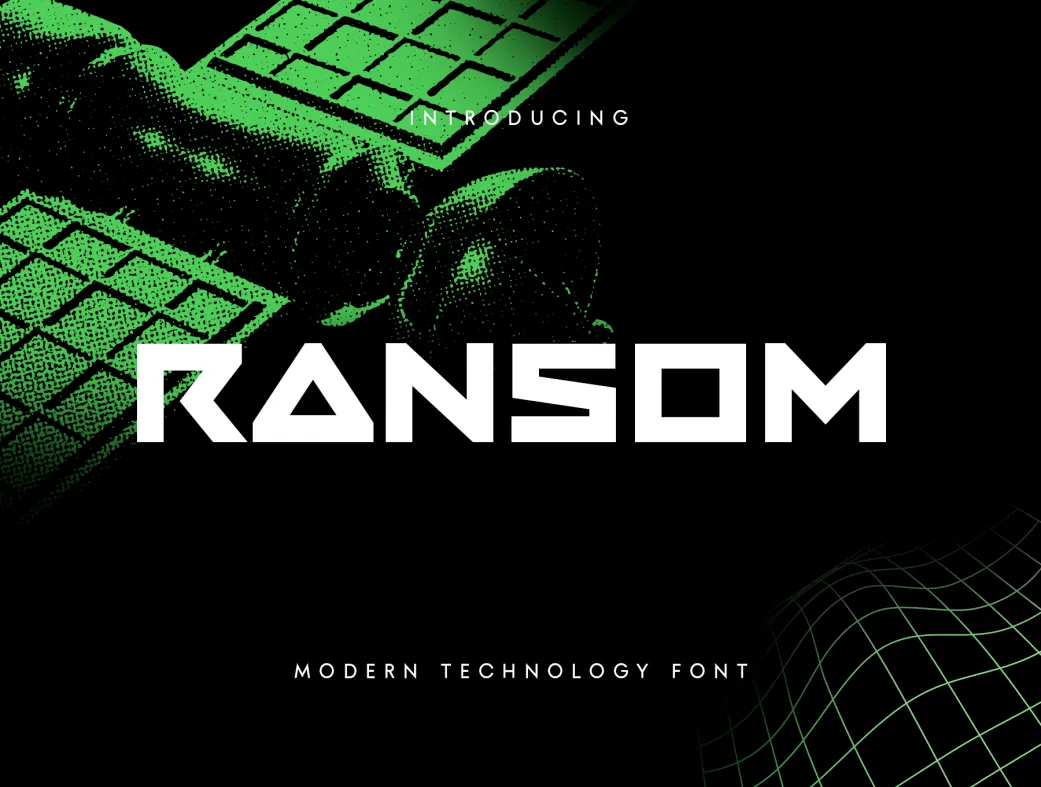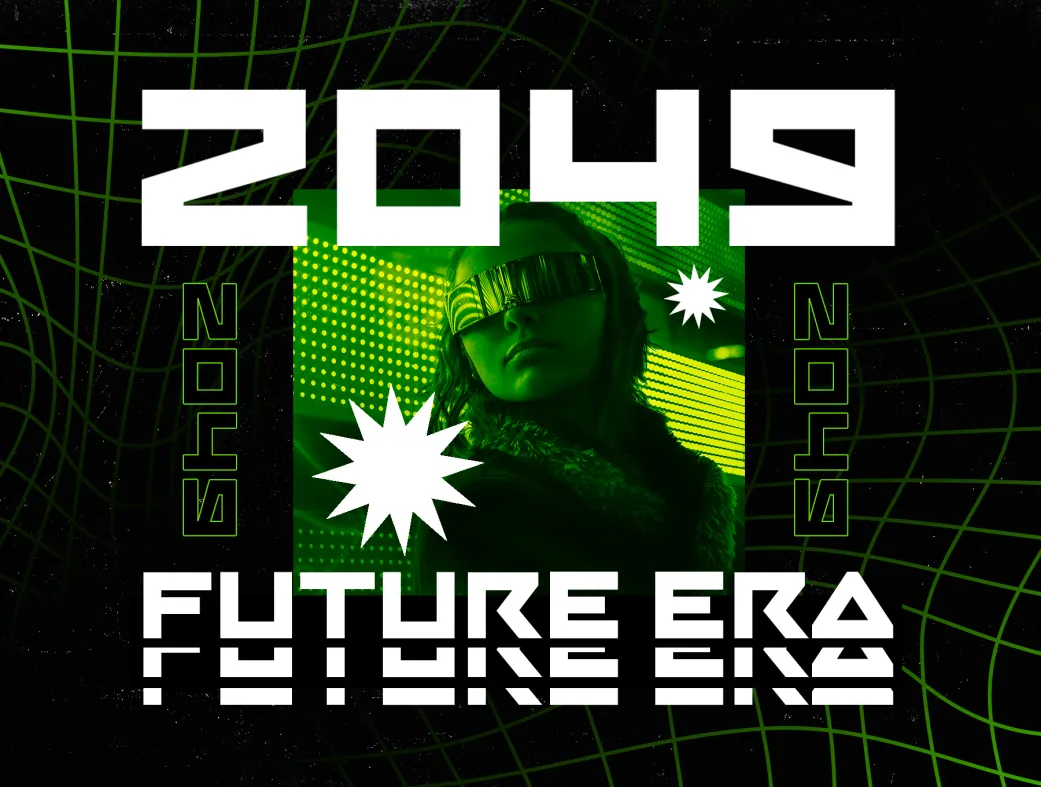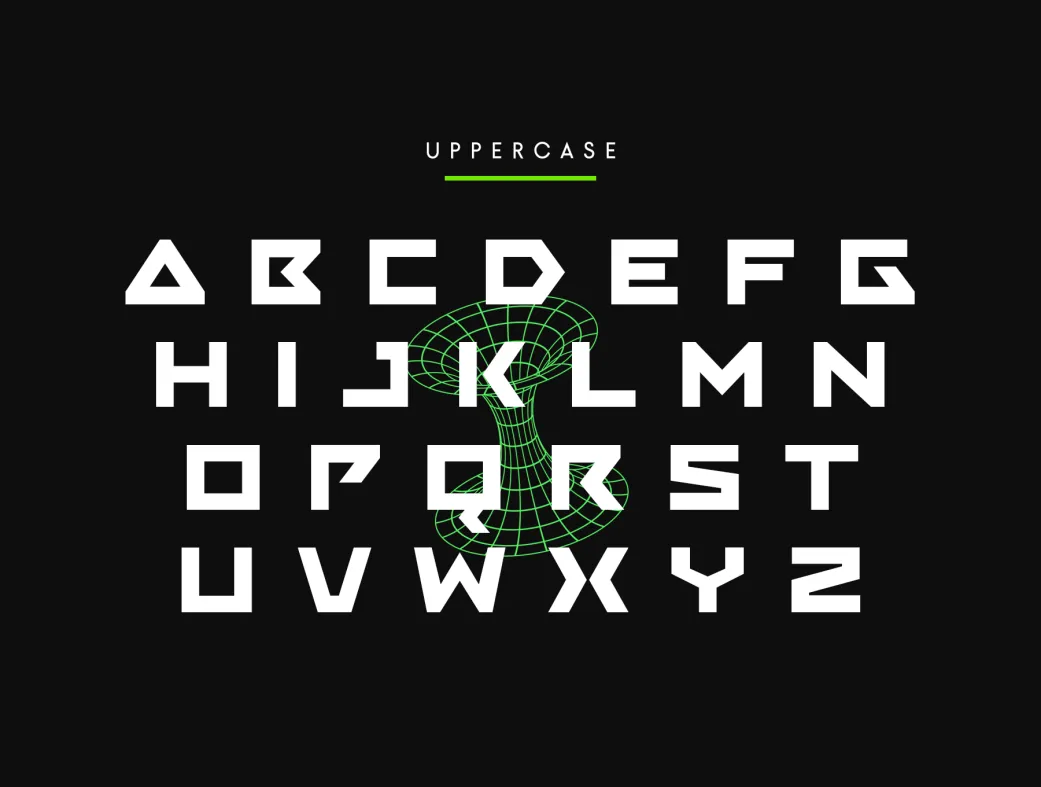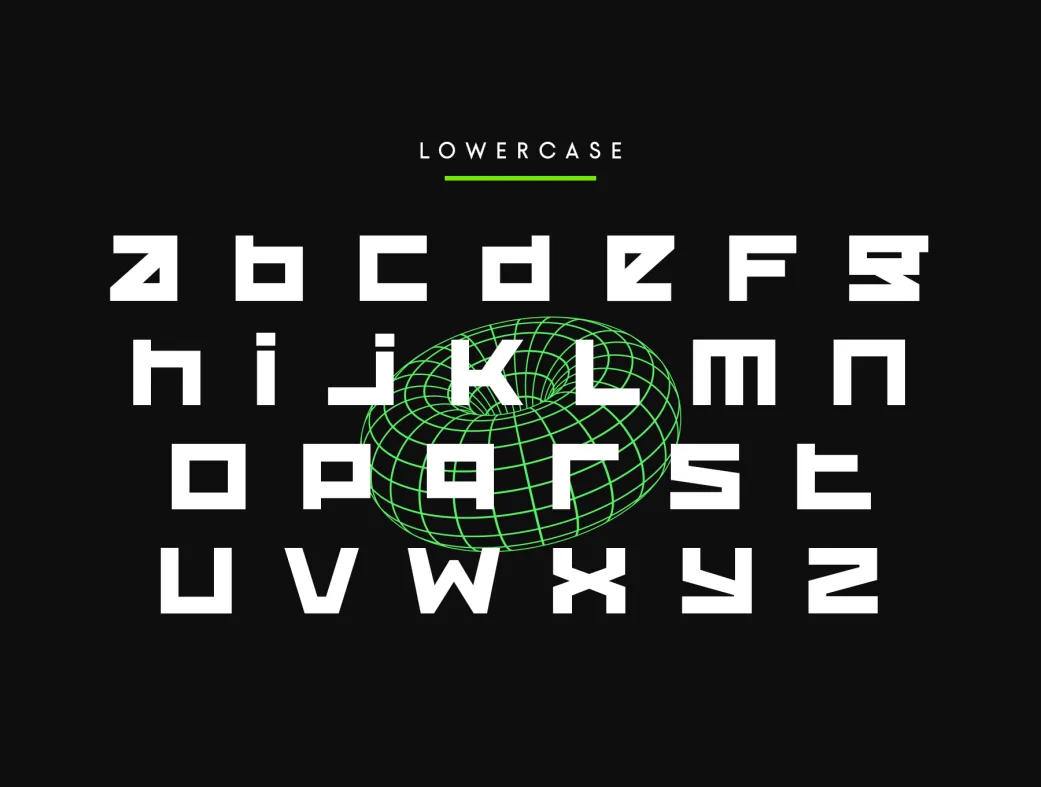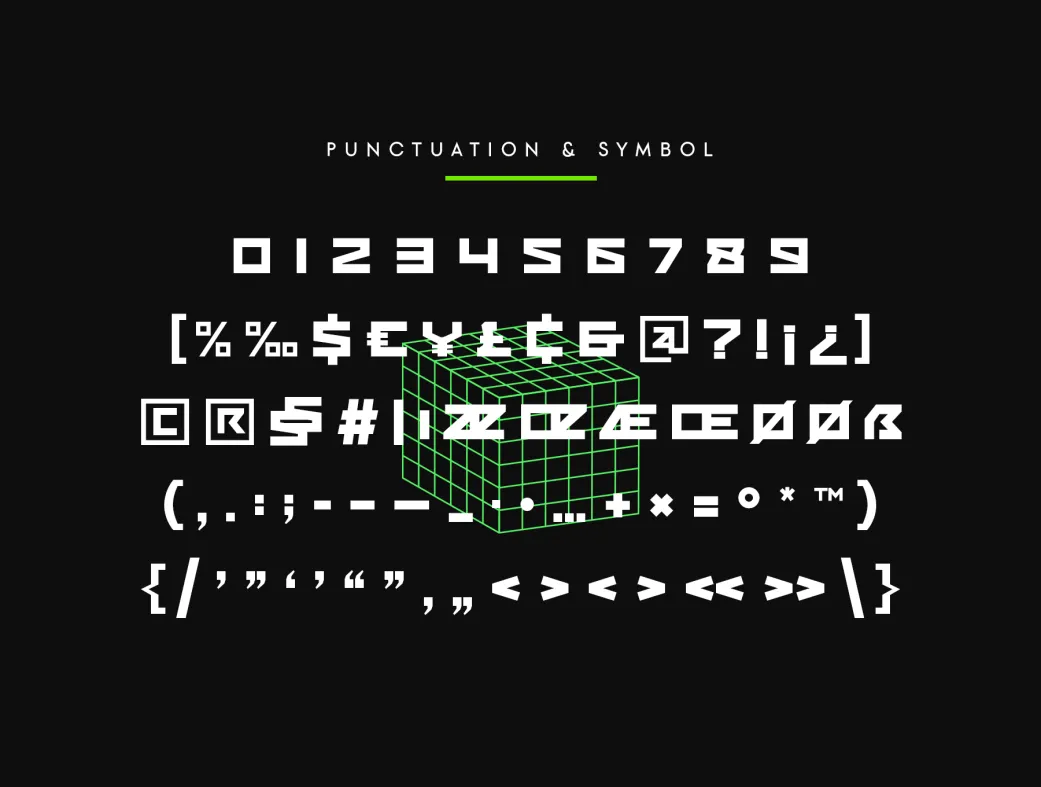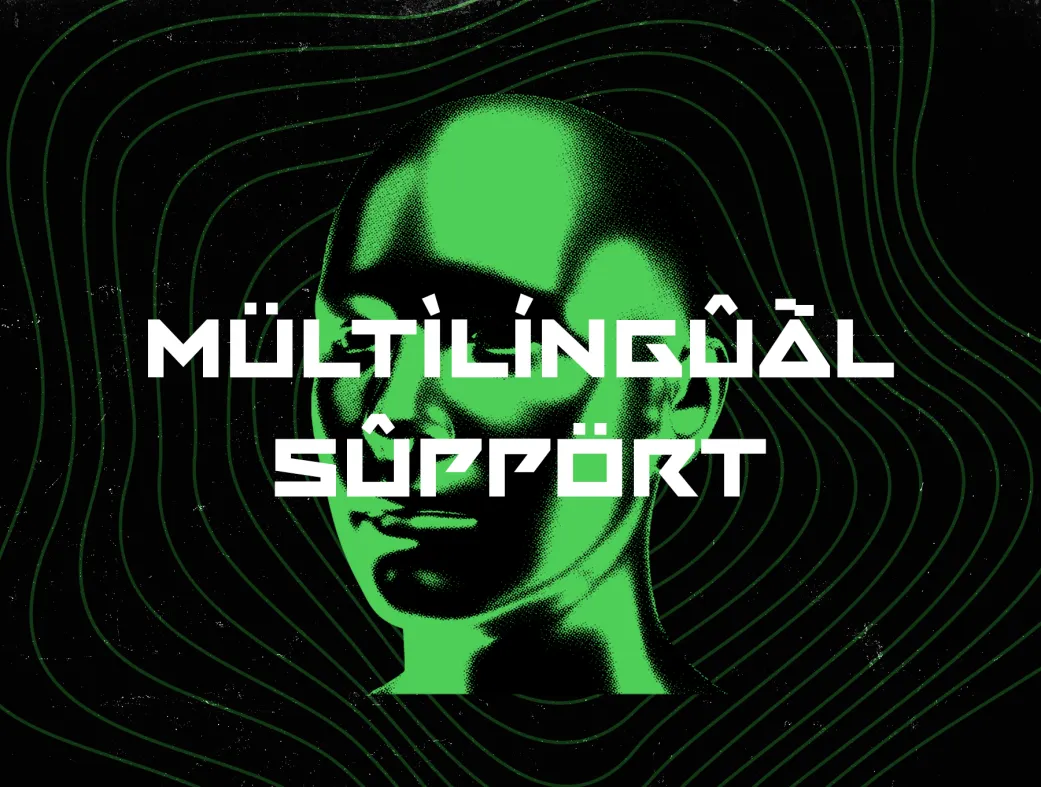
فونت رانسوم - مدرن و تکنولوژیک
فونت رانسوم با سبک آینده‌نگرانه، ایده‌آل برای تیترهای فناوری و طراحی‌های علمی-تخیلی است.
Ransom Font
معرفی فونت رانسوم
فونت رانسوم یک فونت مدرن تکنولوژیک است که به طور خاص برای نیازهای تایپوگرافی برجسته در حوزه فناوری، علمی-تخیلی و طراحی‌های نوین ساخته شده. این فونت با استایل آینده‌نگرانه، طرح‌های شما را به یادماندنی‌تر می‌کند و حس جسورانه‌ای به تیترها و پوسترها می‌بخشد. اگر به دنبال فونتی هستید که تم‌های فناوری، اکشن و آینده را برجسته کند، رانسوم انتخاب ایدئالی برای طراحان خلاق است.
ویژگی‌ها و مزایای فونت رانسوم
فونت رانسوم با تمرکز بر سادگی و قدرت بصری، به شما کمک می‌کند تا پروژه‌هایتان را با کیفیت حرفه‌ای پیش ببرید. این فونت نه تنها سبک مدرن و تکنو دارد، بلکه برای استفاده در وب و چاپ بهینه‌سازی شده و خلاقیت شما را در طراحی‌های فناوری‌محور افزایش می‌دهد. از حروف بزرگ و کوچک کامل تا نمادهای چندزبانه، همه چیز برای ایجاد طرح‌های چشمگیر آماده است.
کاربردهای رانسوم در طراحی‌های آینده‌نگرانه
این فونت عالی برای تیترهای وب‌سایت‌های فناوری، پوسترهای علمی-تخیلی، لوگوهای مدرن و هر پروژه‌ای که نیاز به حس اکشن و نوآوری دارد، مناسب است. طراحان UI/UX می‌توانند از آن در اپلیکیشن‌های موبایل و دسکتاپ برای برجسته کردن عناصر کلیدی استفاده کنند و نرخ تعامل کاربران را افزایش دهند.
فونت رانسوم با این ویژگی‌ها، ابزاری ضروری برای طراحانی است که می‌خواهند در بازار رقابتی برجسته شوند.